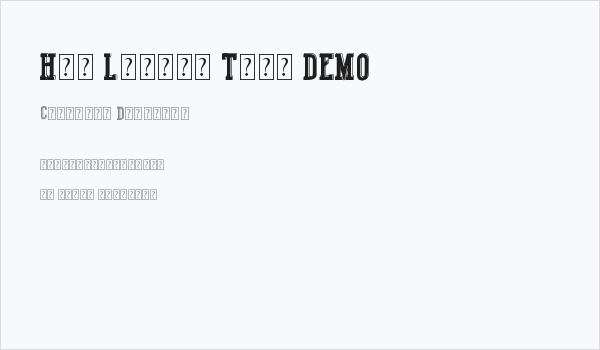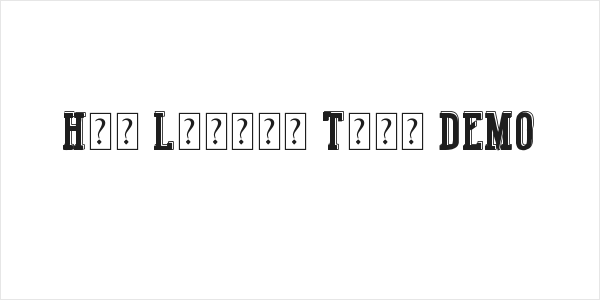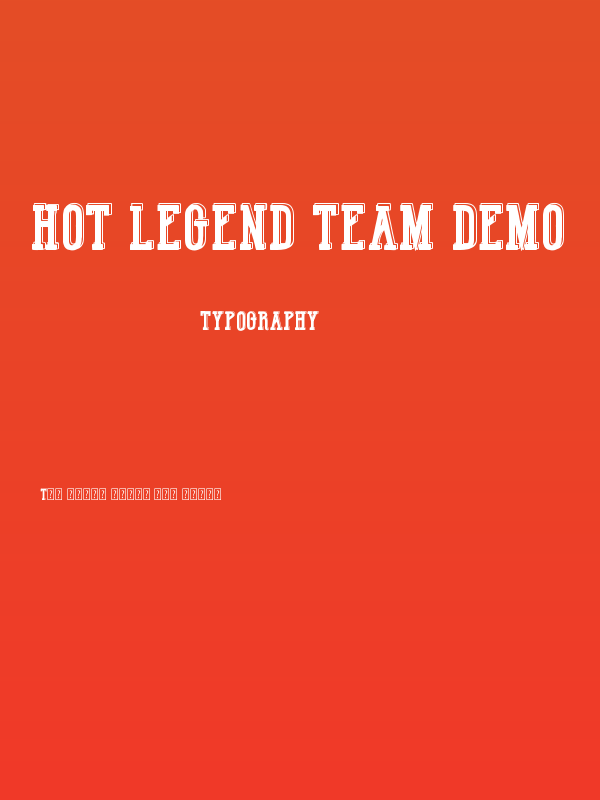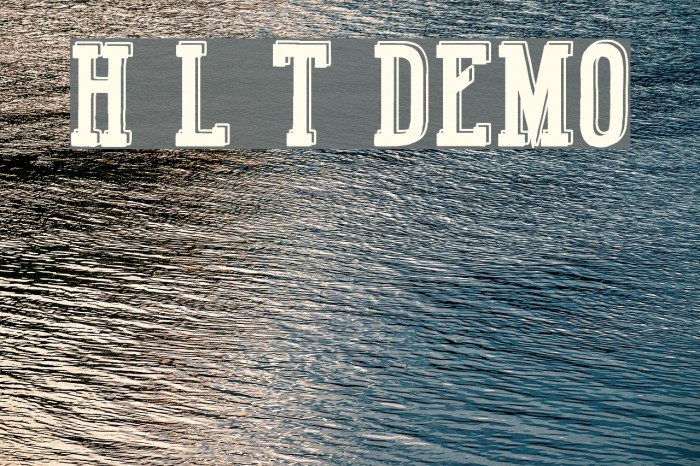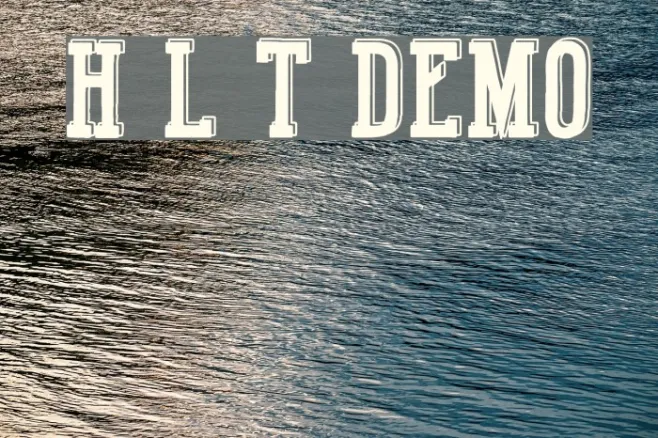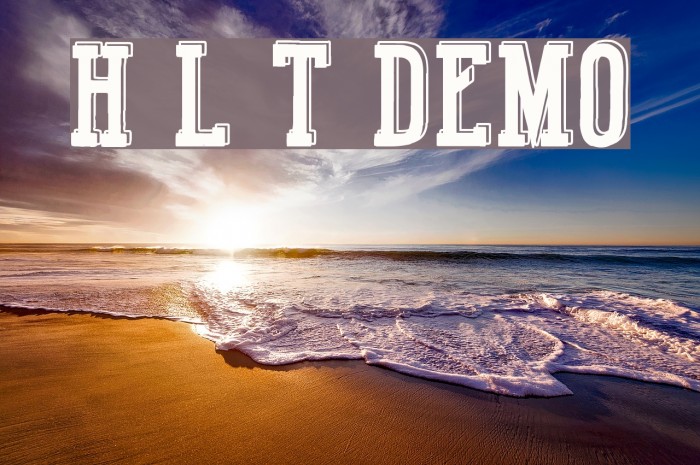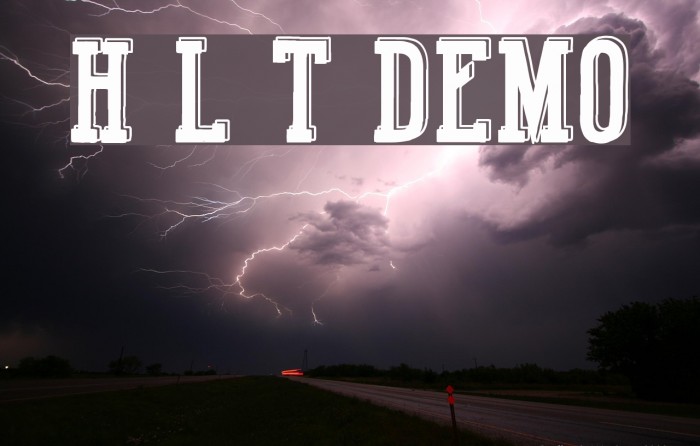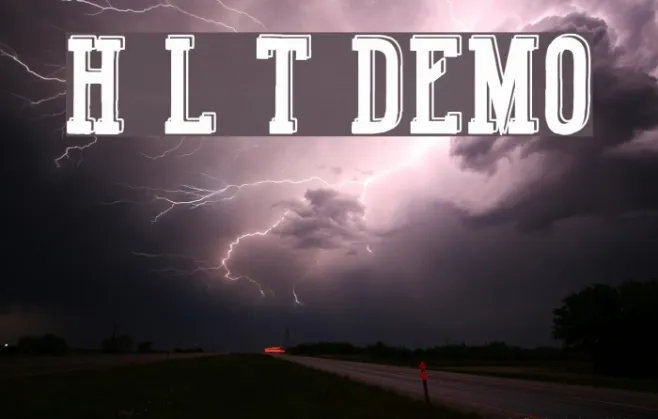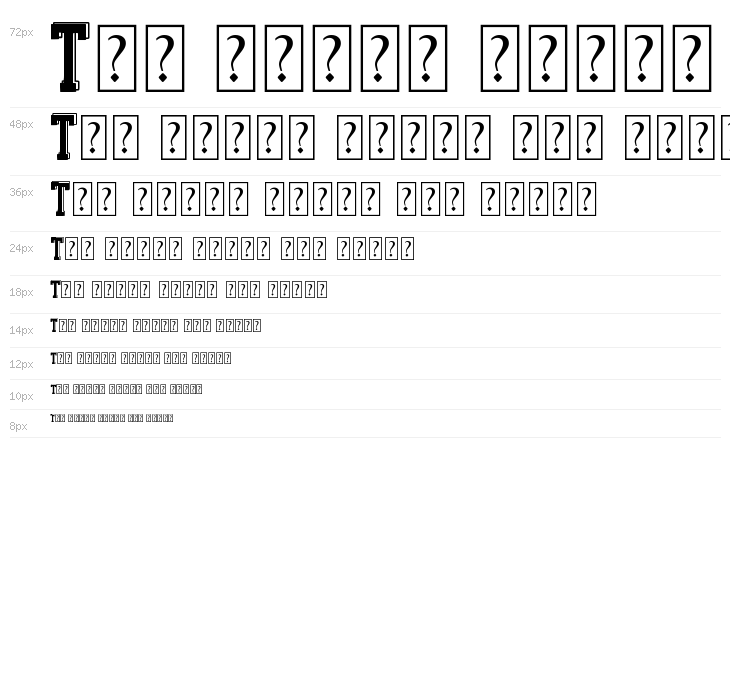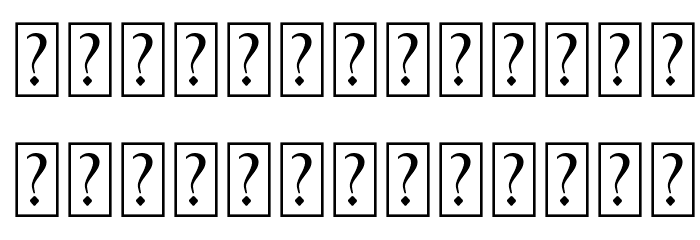
Hot Legend Team DEMO Font
✎ Western
| Categorías | Western |
| Estilo general | Vintage |
| Proyectos propuestos | Ideal for vintage-themed posters, logos, and headlines that require a bold and nostalgic touch. |